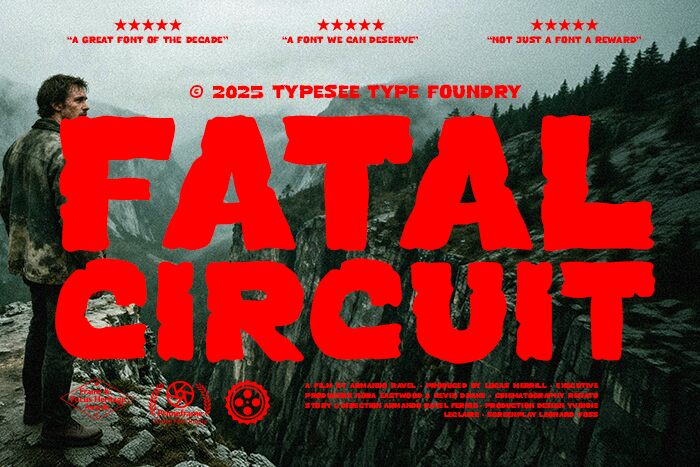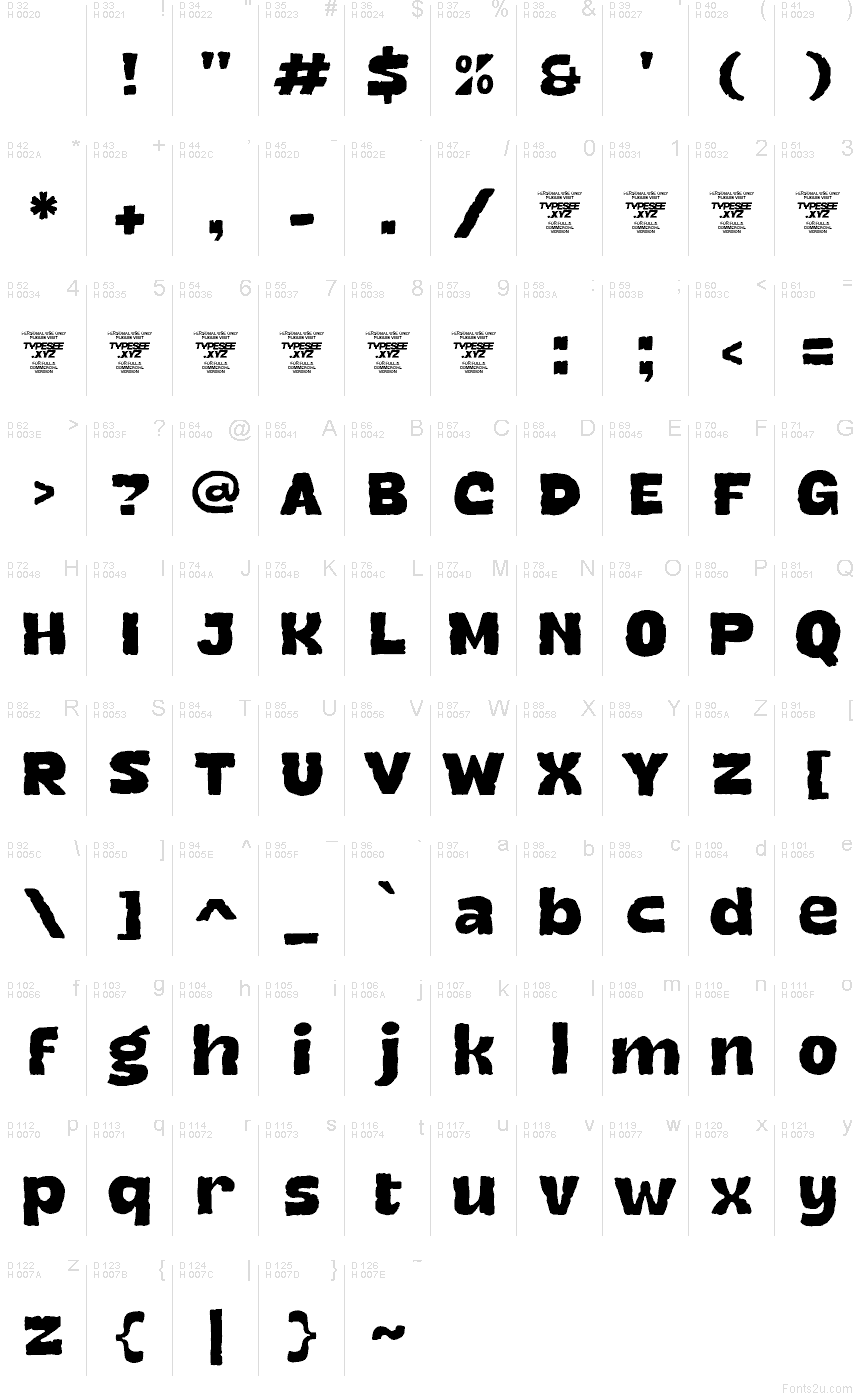
Fatal Circuit от Typesee Type Foundry - это бесплатный эродированный дисплейный шрифт с грубыми, неровными краями и «выбитыми» элементами, которые придают буквам изношенный, поврежденный вид. Формы букв остаются широкими и блочными, но поверхность выглядит скорее поврежденной и хаотичной, чем гладкой или полированной.
Fatal Circuit отлично подходит для постеров, обложек альбомов, хоррор-флаеров, игровых названий и стритвир-графики, поскольку эродированная текстура добавляет выразительности, сохраняя при этом основу строения букв. Этот бесплатный шрифт также хорошо смотрится в редакционных заголовках и акцентных элементах логотипов, когда требуется создать суровый и намеренно небрежный эффект.